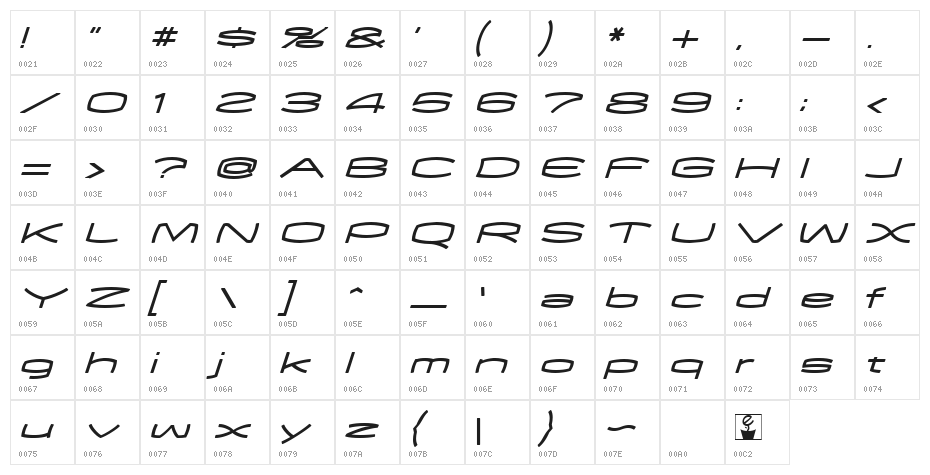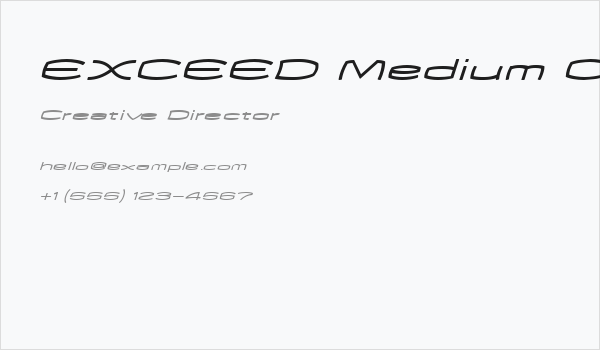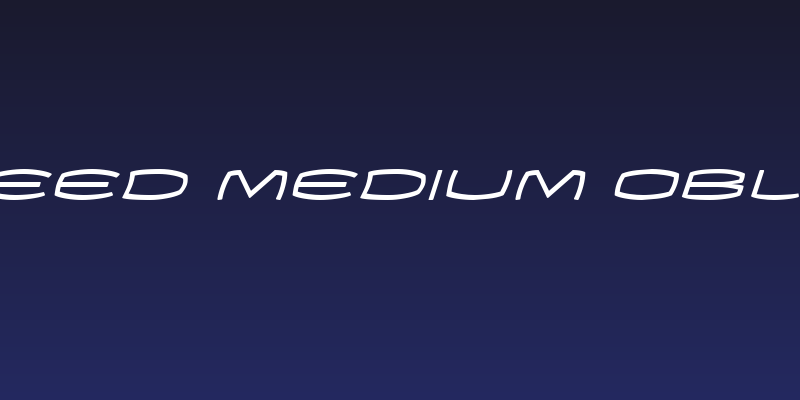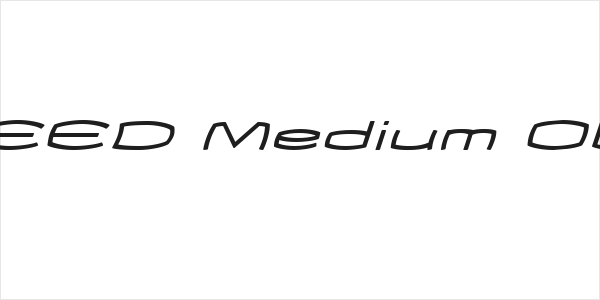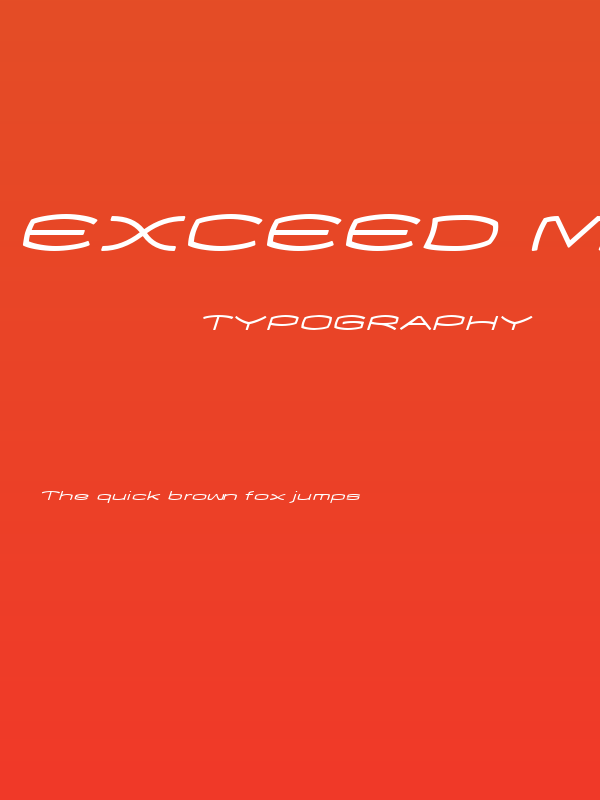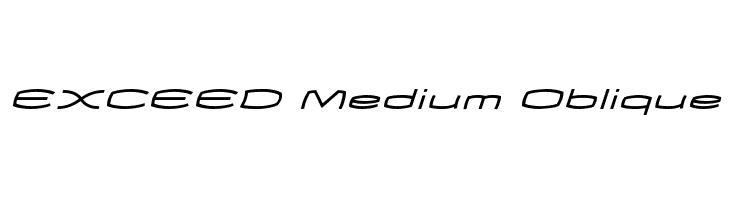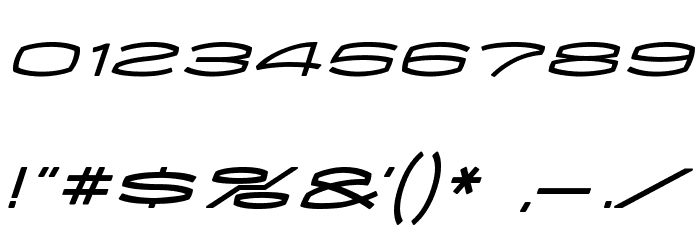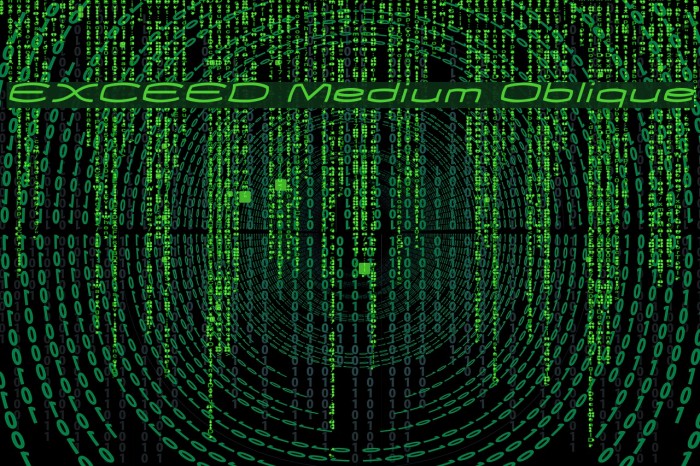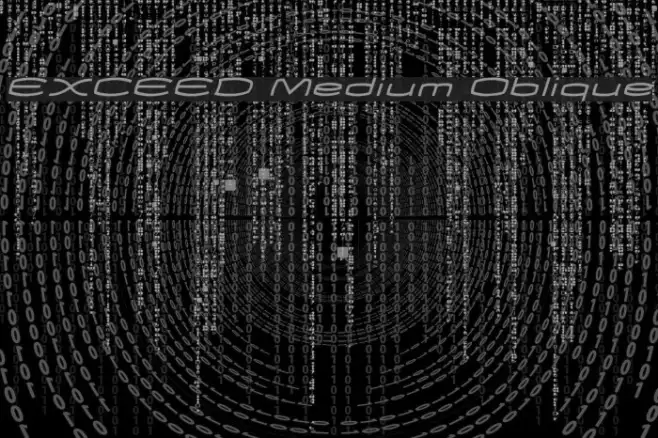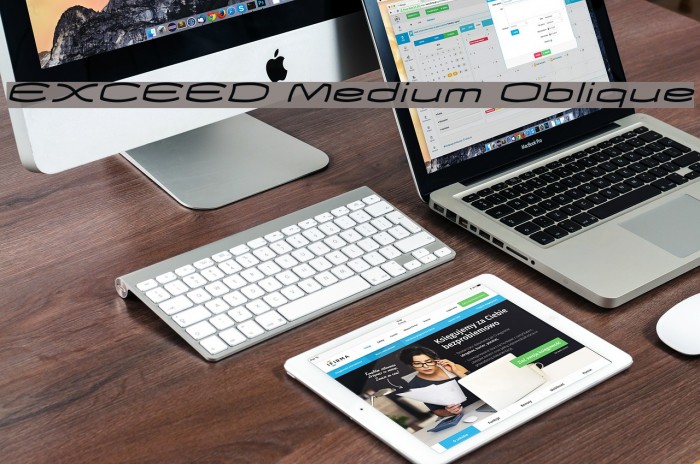
EXCEED Medium Oblique Font
| Categorie | Modern |
| Caso d'uso | Headlines, Logos, Digital Media |
| Progetti proposti | Ideal for branding, advertising, and digital media projects that require a modern and stylish touch. |